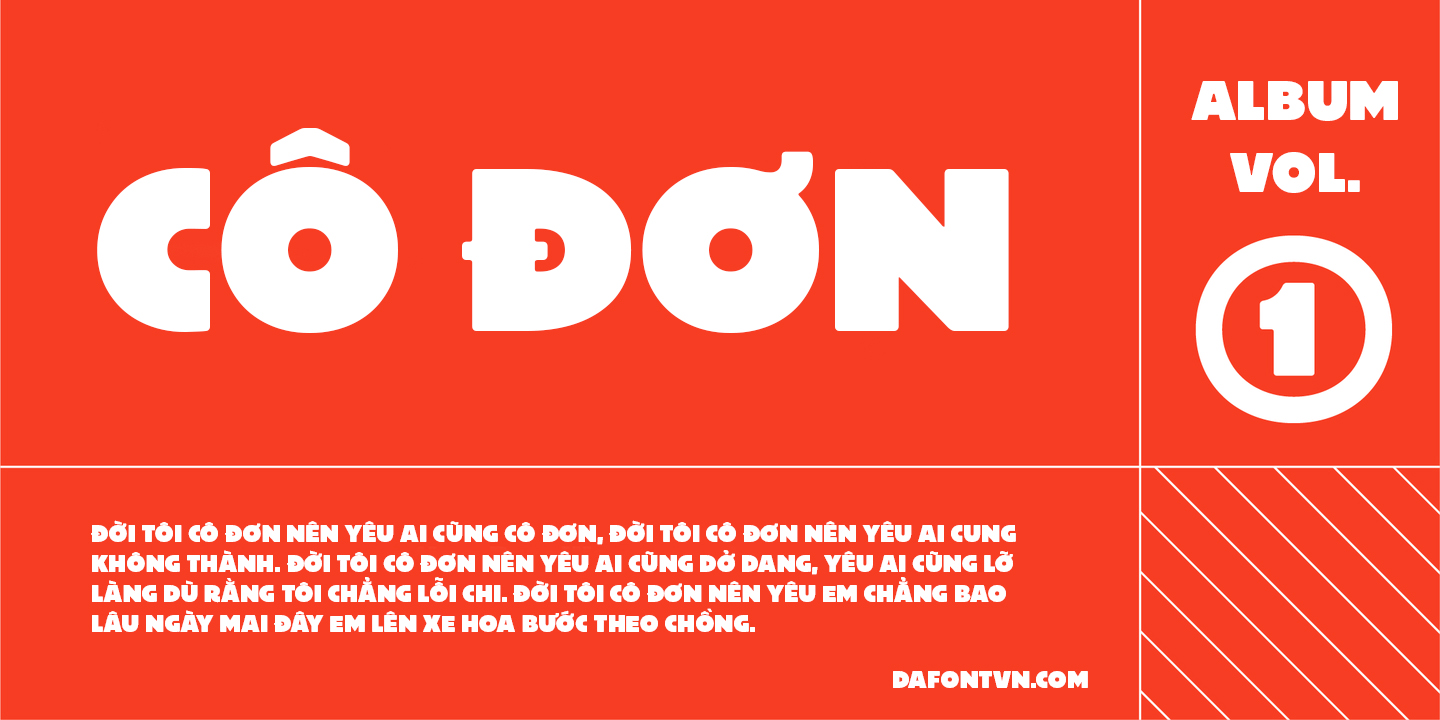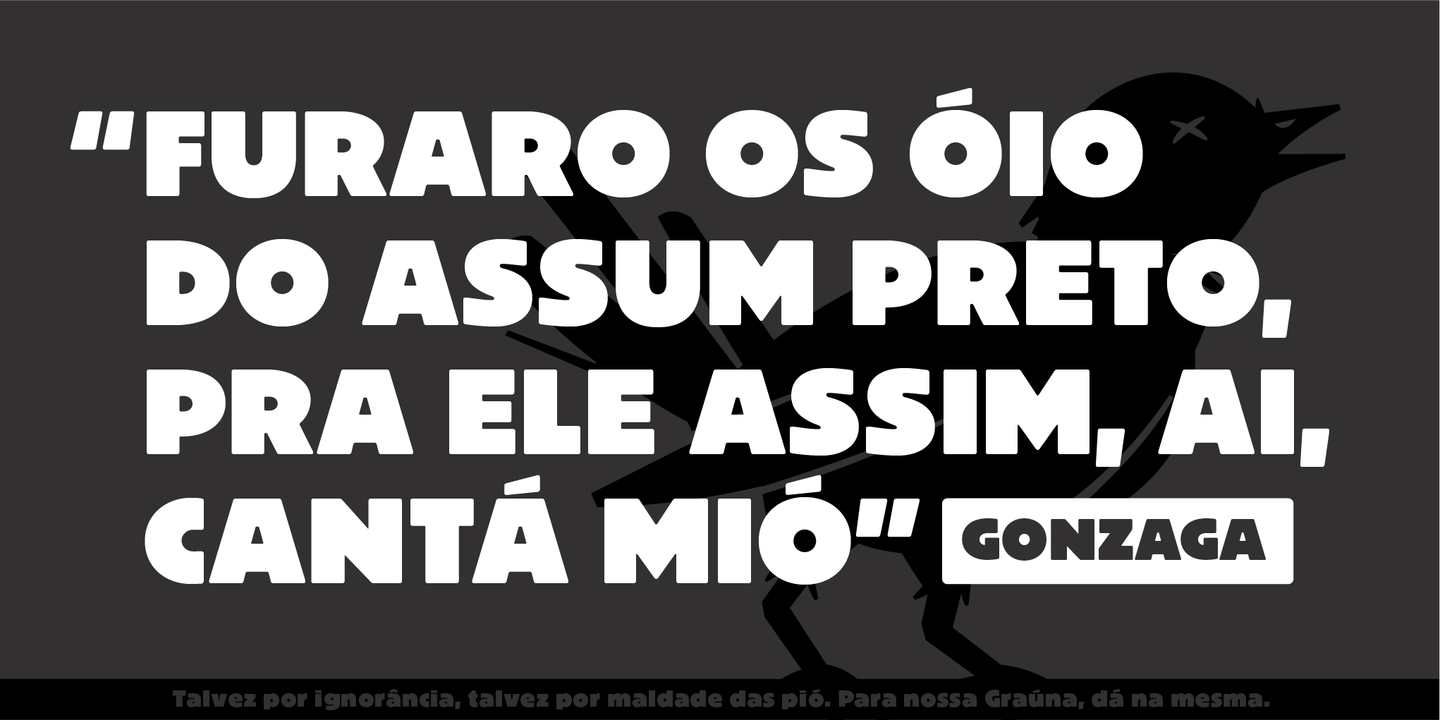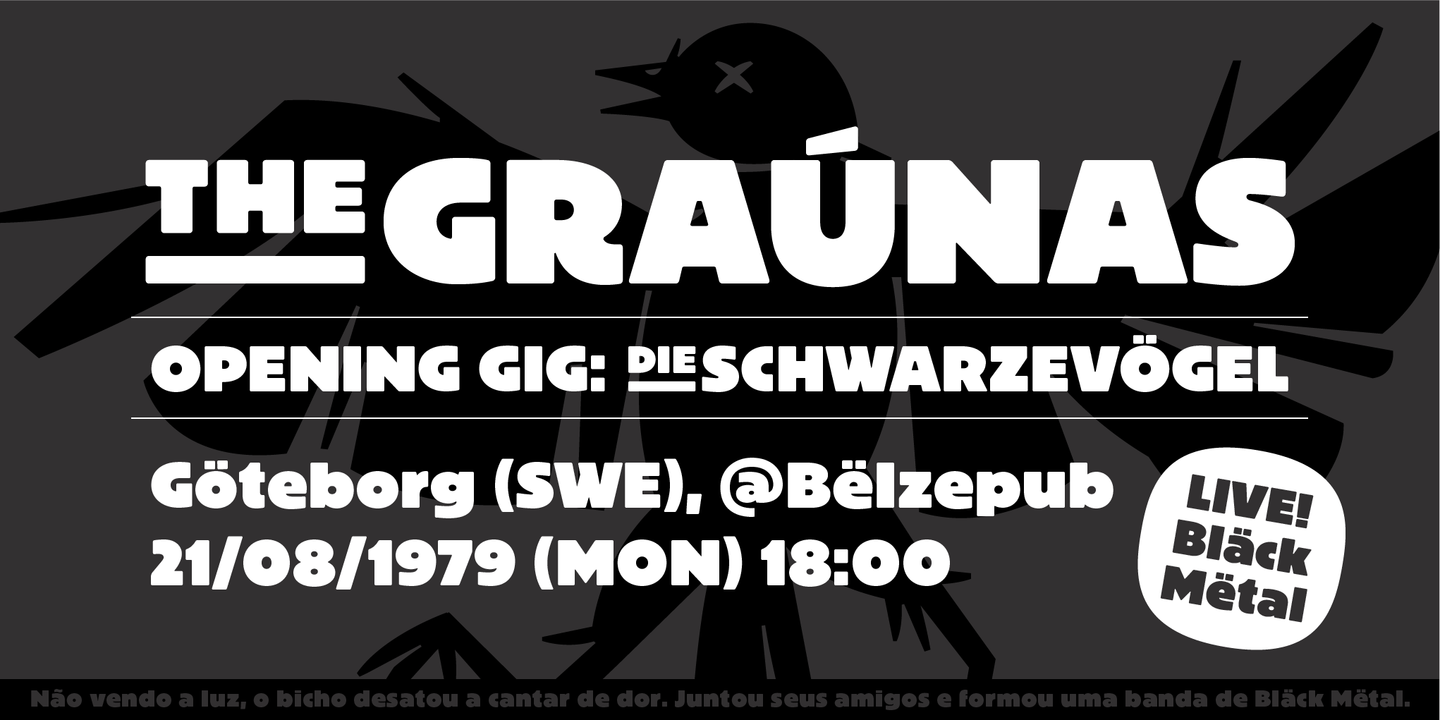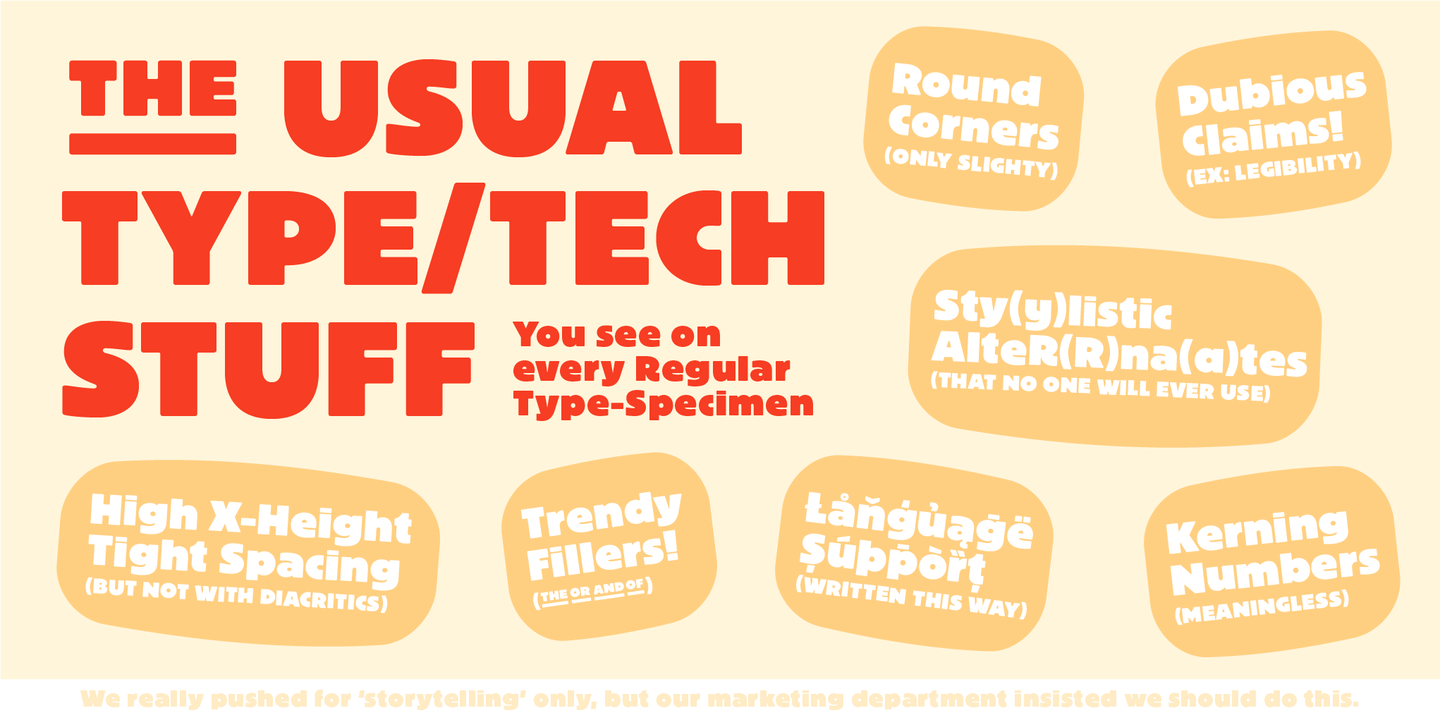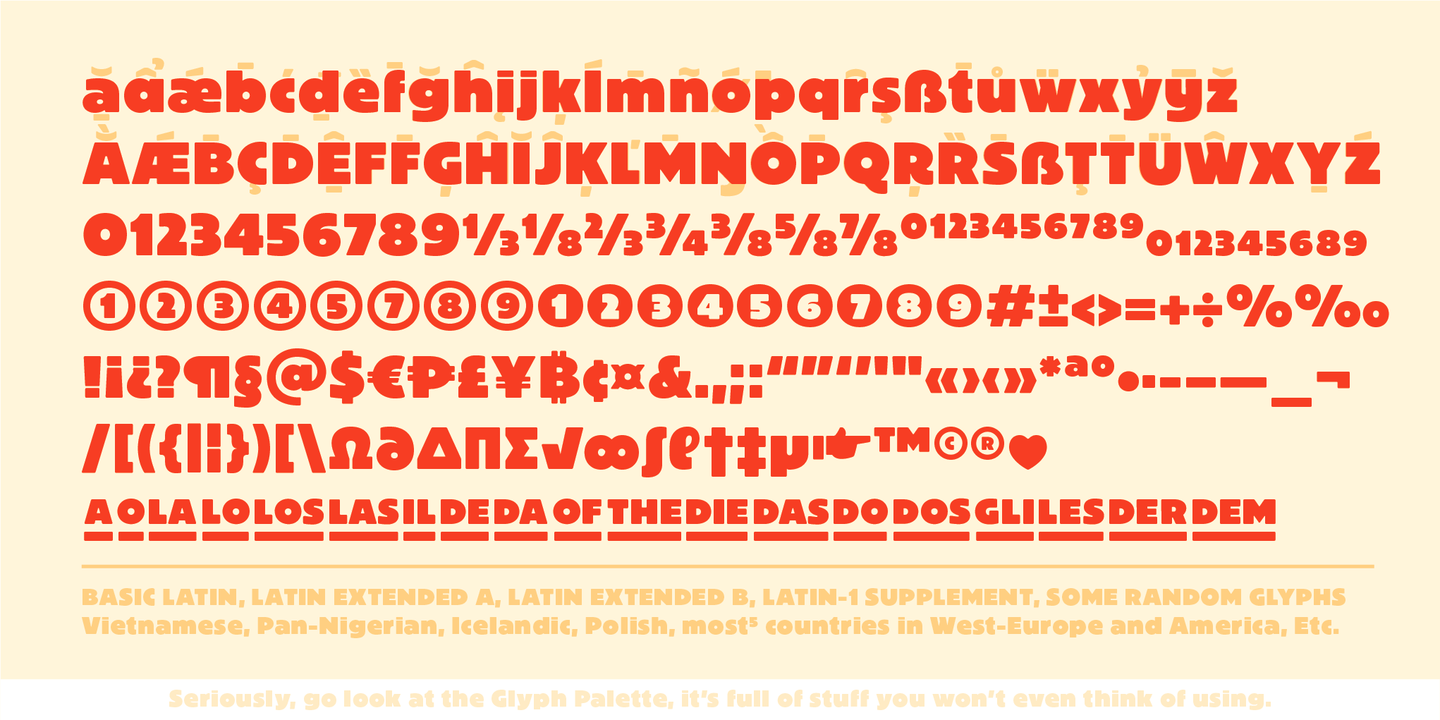
Graúna Việt Hóa là ‘serious typeface’ đầu tiên của Typeóca. Đây là một font chữ phù hợp dành cho các thiết kế tiêu đề hoặc logo bởi các chữ cái được thiết kế với các nét đậm và to.